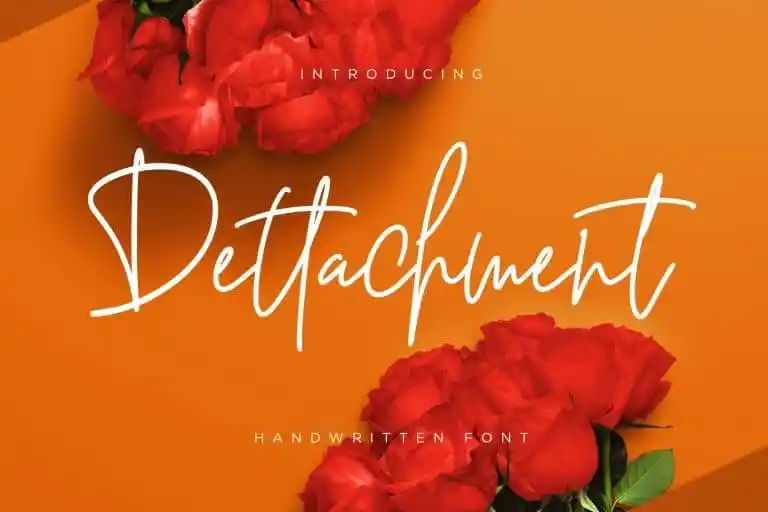
Dettachment Handwritten Font – Download Grátis
A fonte “Dettachment Handwritten Font” é uma elegante combinação entre a simplicidade minimalista e a beleza do traçado handwritten. Ela foi criada pelo Creatype Studio, oferecendo um toque especial com suas curvas únicas e sua linha fluida de tinta inebriante. Este tipo script enriquece qualquer projeto que exija o sabor da escrita à mão, sendo perfeito para iniciativas de marcação, logos, designs de casamento, postagens nas redes sociais, anúncios, embalagens de produtos, designs de produtos, etiquetas, fotografia e até mesmo assinaturas. É uma opção ideal para qualquer trabalho que seja beneficiado pela elegância e personalidade da escrita à mão, criando um toque único e original em qualquer projeto.